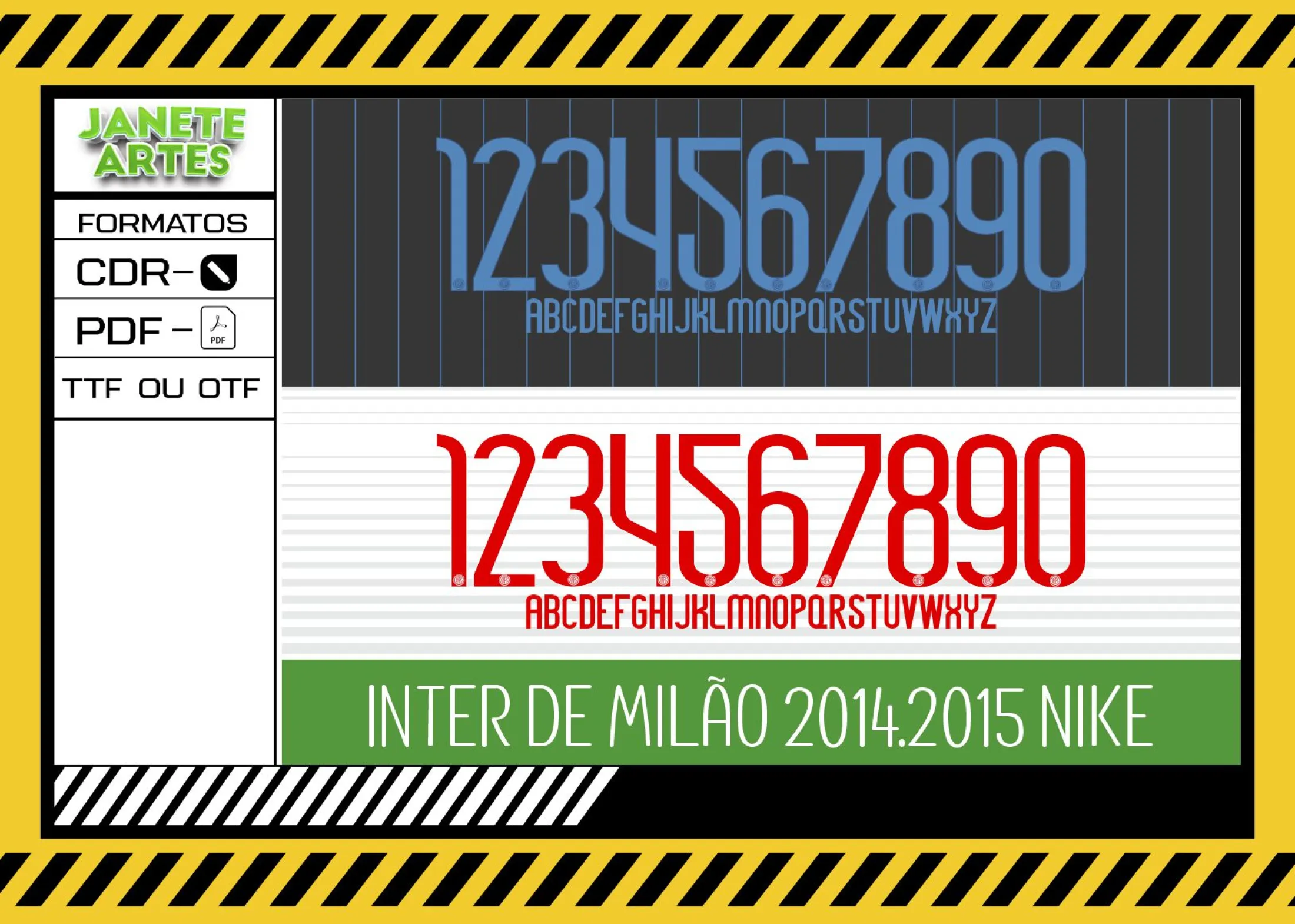
Fonte de Time Tipografia Inter de Milão 2014 - 2015
Conheça a Fonte de Time Tipografia Inter de Milão 2014 - 2015, arquivo digital perfeito para personalizar camisetas com design exclusivo da lendária tipografia do time italiano.
Uma história de paixão e design
Imagine um grupo de amigos apaixonados por futebol que decidiu criar suas próprias camisetas para torcer pelo Inter de Milão durante a temporada 2014 - 2015. Sem encontrar nada que tivesse a tipografia original daquele período, eles descobriram o Arte Fonte de Time Tipografia Inter de Milão 2014 - 2015. Com ele, conseguiram personalizar suas camisetas com o logo no peito e a estampa grande nas costas, vivenciando juntos emoções únicas em cada jogo.